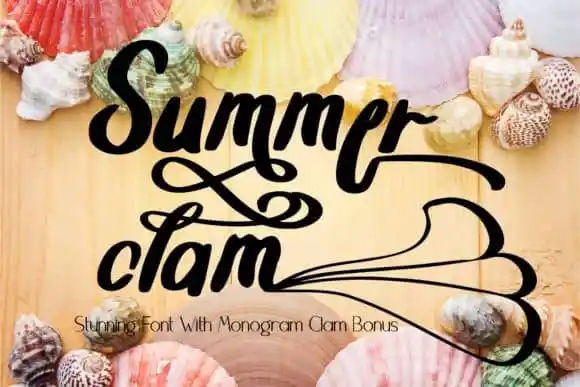
Summer Clam Calligraphy Font
A fonte Summer Clam Calligraphy é uma elegante mistura de letra feita à mão, perfeita para tornar qualquer projeto irresistivelmente atraente e destacável! Ela foi criada pelo designer setiyadissi através do site 99designs. Este design gráfico, inspirado no estilo da calligrafia, mantém suas influências clássicas ao mesmo tempo que parece contemporâneo e atual. Com uma grande variedade de recursos incluindo alternativas de letras e ligaturas, esta fonte cativa todos os gênios criativos – desde as assinaturas e títulos até o estilizado papel, oferecendo flexibilidade para várias ideias. Ela também foi codificada PUA, permitindo que você facilmente acesso todas as cute glyphs e swashes de forma simples e prazerosa. Engane-se se pensasse que a fonte Summer Clam Calligraphy não era única. Com um design criativo, personalizado e vibrante, ele é perfeito para qualquer projeto gráfico.